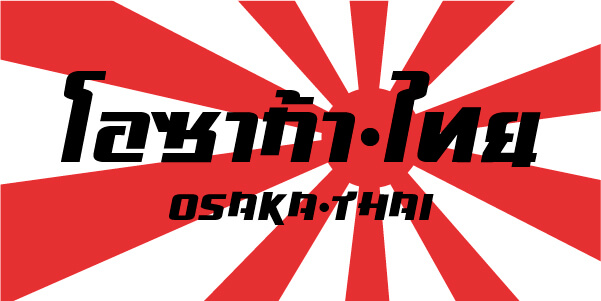
โอซาก้า-ไทย™ (Osaka-Thai™)
โอซาก้า-ไทย™ (Osaka-Thai™) ซึ่งเป็นฟอนต์ตัวแรกของผมที่ได้จัดทำให้เป็นไฟล์ฟอนต์ (.ttf, .otf, ฯลฯ) เนื่องจากเมื่อก่อนได้ทำอักษรในแบบต่างๆไว้ใช้ในงานกราฟิก, สิ่งพิมพ์, สติ๊กเกอร์ ทำแบบเป็นตัวๆแต่ไม่ได้ทำทุกตัวอักษร เวลาใช้งานก็นำมาเรียงในโปรแกรมของ Adobe ซึ่งค่อนข้างไม่สะดวกเท่าไร
ต่อมาจึงได้หาข้อมูลการทำฟอนต์จากในฟอรั่มของพี่ๆสมาชิก f0nt.com แล้วจึงได้มาจัดทำให้เป็นไฟล์ฟอนต์ (.ttf, .otf, ฯลฯ) เพื่อความสะดวกในการใช้งาน ฟอนต์โอซาก้า-ไทย™ (Osaka-Thai™) เป็นแบบตัวพิมพ์ที่ออกแบบ จัดทำ และแจกฟรี โดยสามารถนำไปใช้ในงานออกแบบได้ ห้ามเอาไปขายในเชิงพาณิชย์นะครับ หรืออยากสนับสนุนฟอนต์เคทีสมาน โอซาก้า ของพี่สมานติดต่อได้ที่ www.facebook.com/smarnfont
+ แรงบันดาลใจจากฟอนต์ Osaka Sans Serif โดย Vic Fieger
+ Inspired from Osaka Sans Serif by Vic Fieger